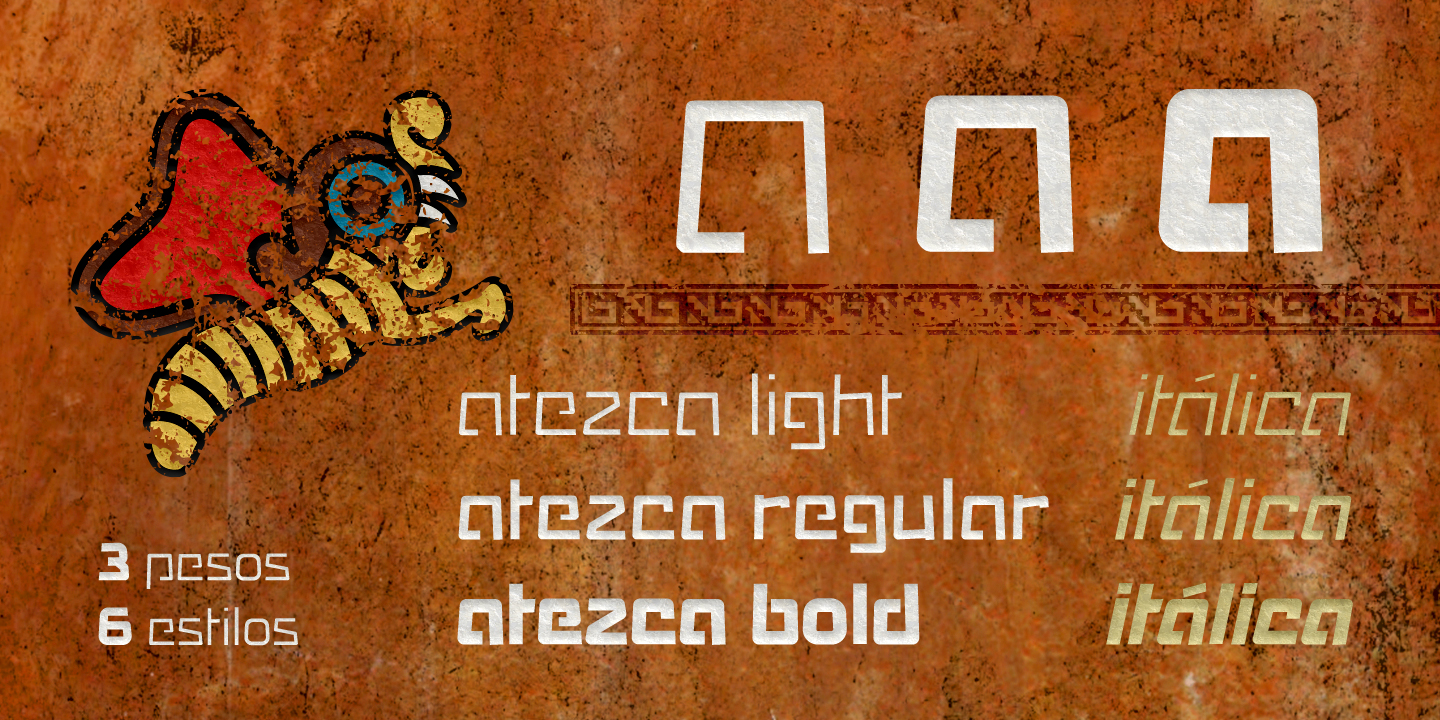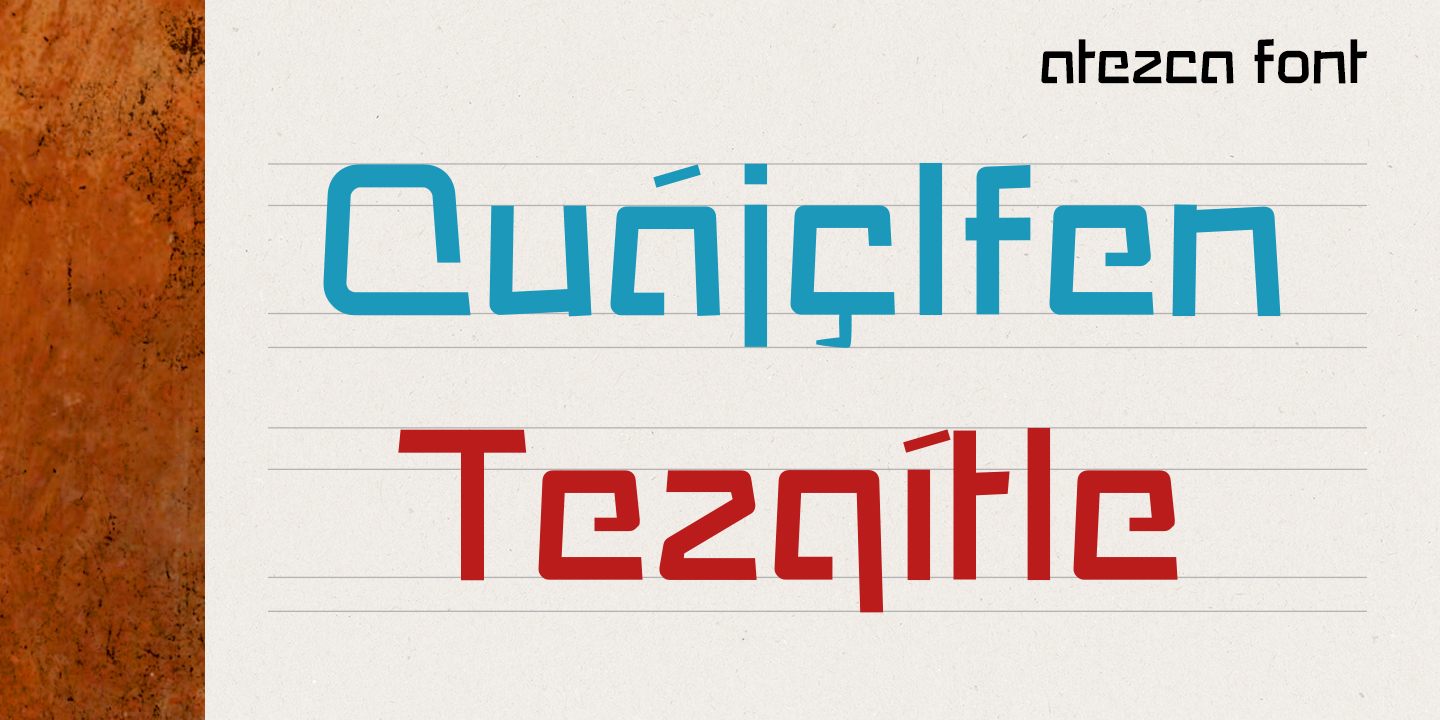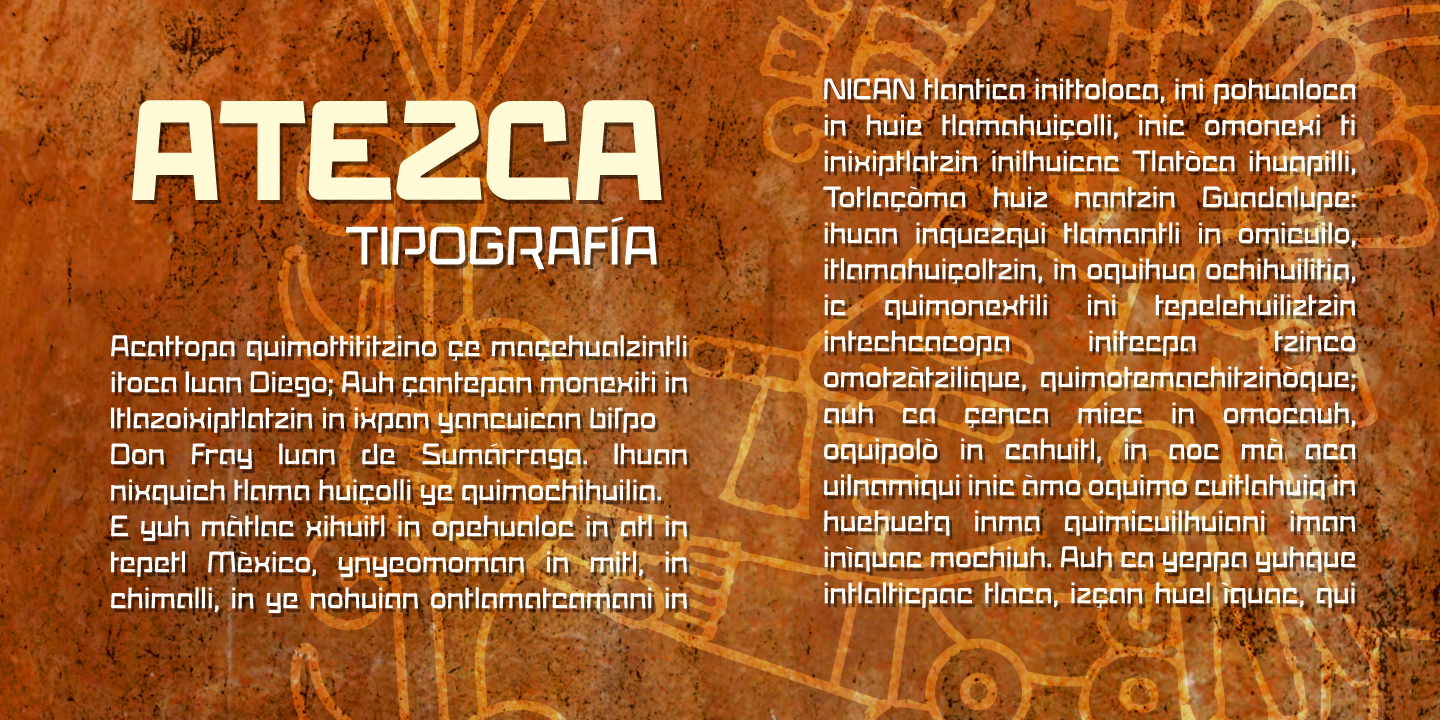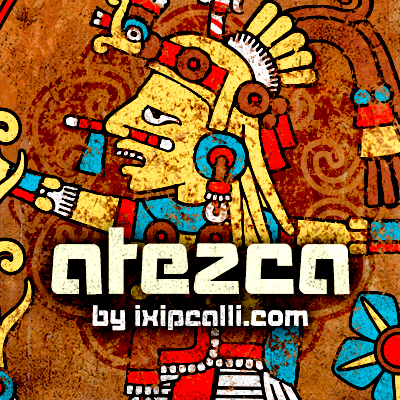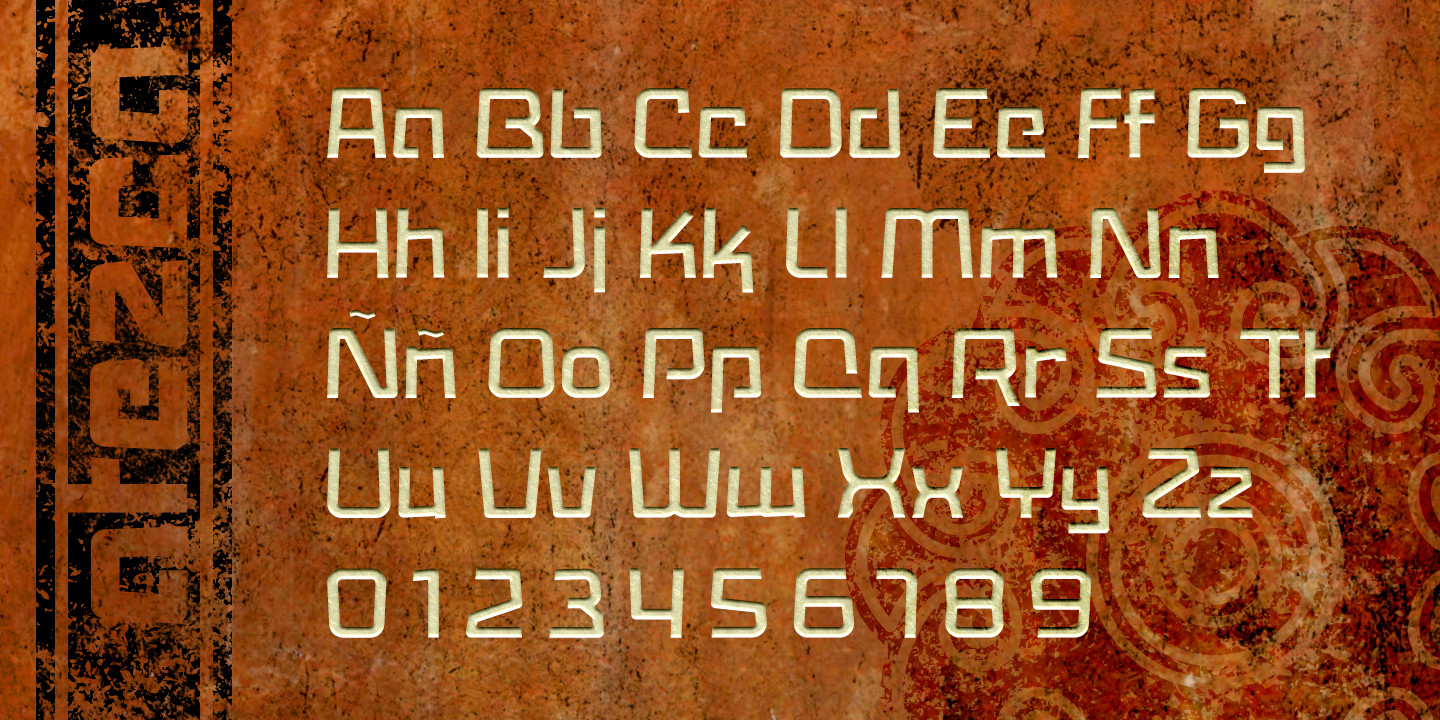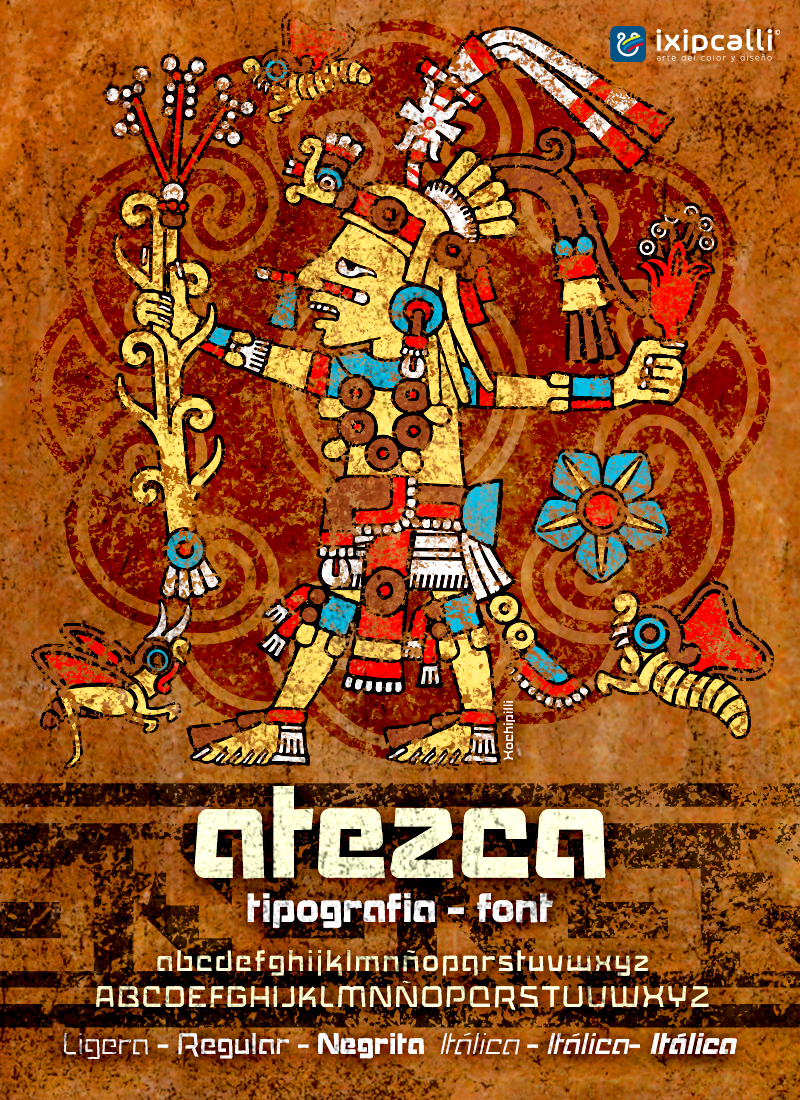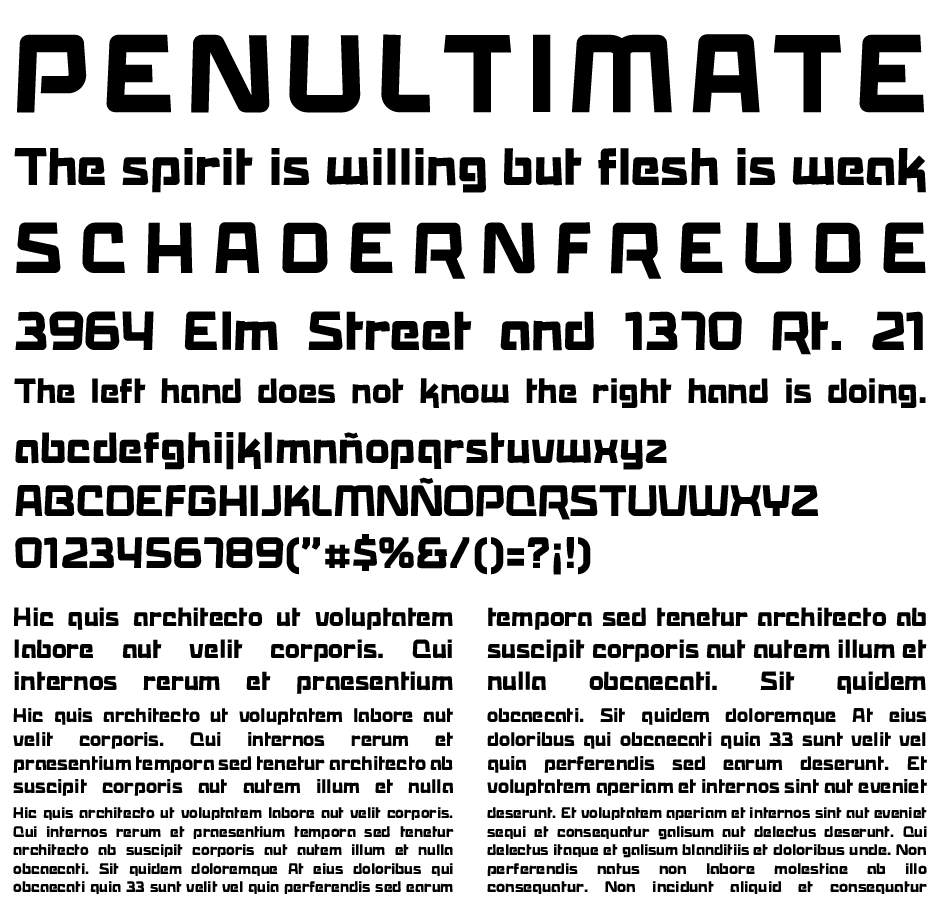
atezca
Descripción:
(2024) - Atezca es una tipografía inspirada en el estilo mesoamericano de la zona central de México. Aunque no muestra las clásicas grecas de los diseños mexicanos «aztecas», su estilo cuadrado, recto y geométrico, esta perfectamente acoplado para su uso en proyectos donde se requiera una visualización caricaturesco, retro, futurista, tecnológico, informal o bien, con un poco de ajuste en el espaciado, se emplea formalmente.
Esta tipografía posee tres pesos (ligera, regular y negrita) junto con sus estilos de apariencia itálica.